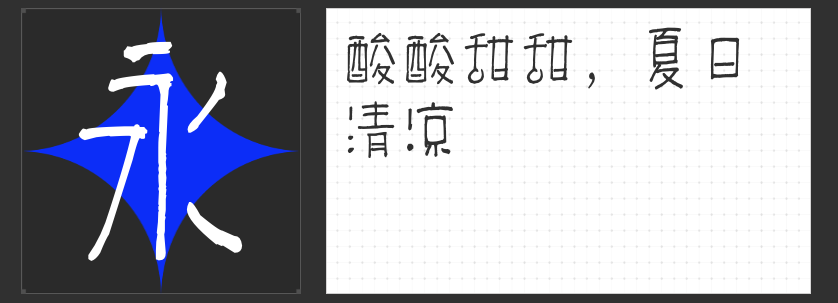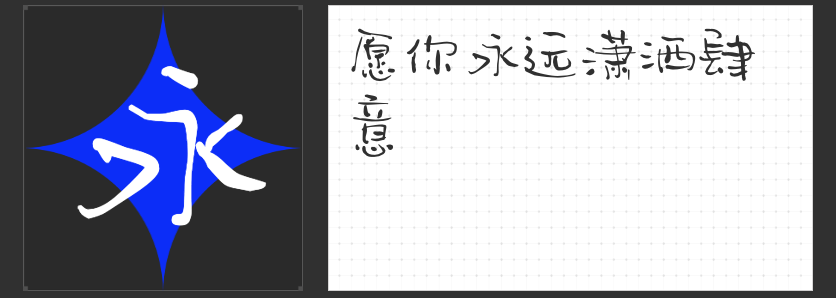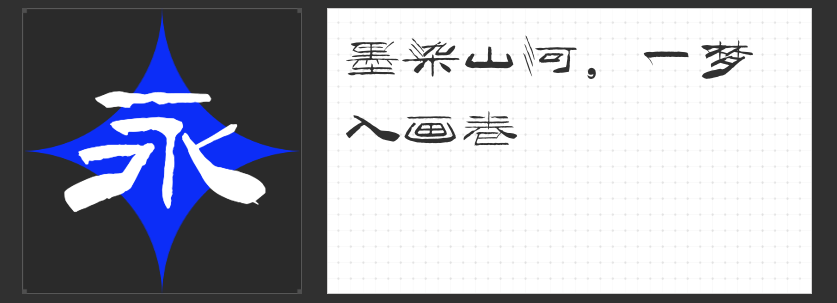
挥洒创意,四款独特手写字体引领设计新风尚
在这个视觉传达日益重要的时代,字体的选择不仅仅是文字的表现形式,更是设计师情感与品牌性格的传递媒介。今天,我们要向大家推荐四款独具特色的手写字体,它们以其非凡的设计理念和艺术魅力,在众多字体中脱颖而出,为您的设计项目增添一抹亮色。
1. 云书法铁笔隶书体
“云书法铁笔隶书体”是一款别具一格的手写字体,其最显著的特点在于字形的宽扁结构,横画长而竖画短,巧妙地将传统的圆润笔触转化为方形与直线的结合,使得每一个字都充满了力量感。笔画之间的粗细变化以及转折处的细腻处理,赋予了字体更加丰富的层次感。这种庄重方正而又不失古朴之美的风格非常适合用于传统文化相关的书籍装帧、海报设计及各类正式场合的排版应用。
2. 云书法永刚漆书体
“云书法永刚漆书体”则以它那厚重的笔触和清晰从容的撇捺展现出了非凡的艺术效果。每个字仿佛都有生命一般跃然纸上,灵性十足。该字体的框架结构鲜明,整体风格统一和谐,无论是用于包装设计还是广告宣传,都能够给人留下深刻印象。尤其适合于那些追求高雅品味且注重细节表达的设计项目。
3. 小豆岛默陌枝桠简
“小豆岛默陌枝桠简”是一套极具东方韵味的手写字体,它将传统书法的写意精神融入现代设计理念之中。通过不同速度与力度下的运笔动作,创造出如枯枝般自然生长的文字形态,既有水墨画般的意境美,又不失时尚感。此字体适用于各种文化活动宣传、文艺作品封面制作等领域,能够帮助设计师更好地表达出作品的情感内涵。
4. MyFont柠檬简
对于那些希望营造欢快、轻松氛围的设计项目来说,“MyFont柠檬简”无疑是一个理想的选择。这套字体打破常规,重新定义了文字的结构与布局,使每个字符都充满了跳跃性和生命力。简洁明快的线条勾勒出俏皮可爱的形象,非常适合用于儿童读物、休闲食品包装以及社交媒体内容创作等多个场景。
以上四款字体各具特色,不仅能够满足设计师们在不同应用场景下的需求,同时也代表了当今手写字体设计领域的最新趋势。希望通过这些字体的应用,能够让我们的设计作品更加丰富多彩,更具吸引力。